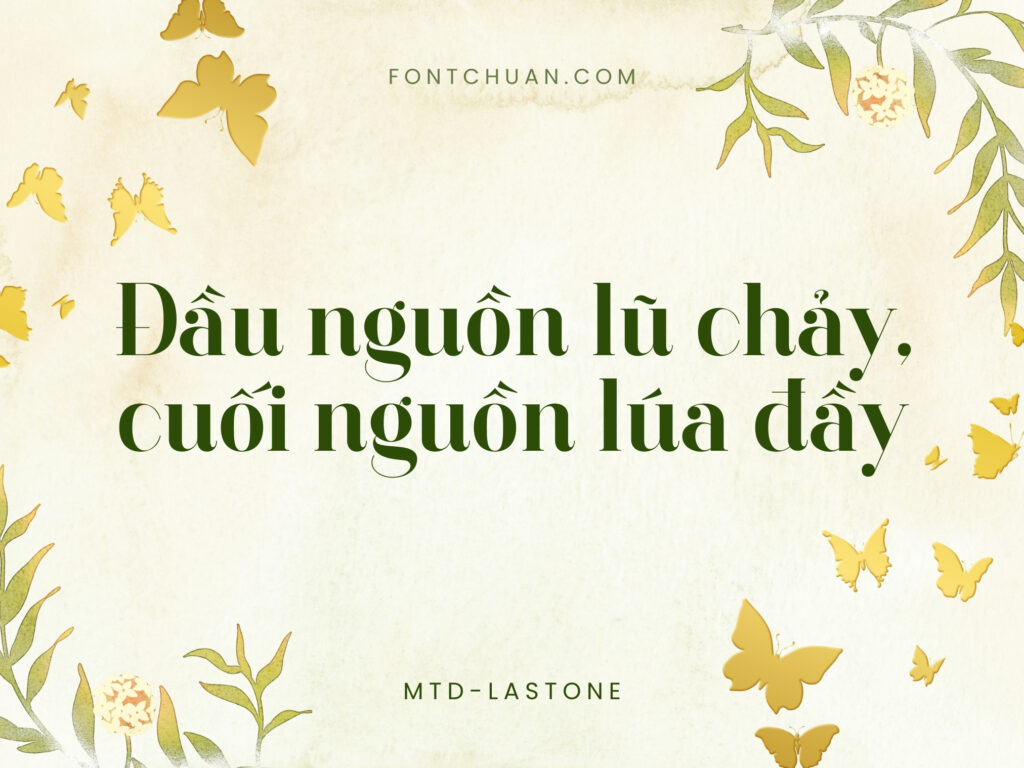
Font MTD Lastone Việt Hóa
Font MTD Lastone là một kiểu chữ hiển thị độc đáo mang hơi hướng hiện đại pha lẫn cổ điển, được thiết kế bởi Drizy Studio và Việt hóa bởi Mộc Hạ. Font hỗ trợ đầy đủ tiếng Việt và hơn 90 ngôn ngữ khác, tạo điều kiện thuận lợi cho việc sử dụng trong nhiều loại dự án thiết kế quốc tế. Font này đã được các thành viên của Font Chuẩn chọn lọc và ứng dụng vào thực tế thiết kế, đặc biệt trong các lĩnh vực sáng tạo cần sự mới lạ và cá tính thị giác.
MTD Lastone gây ấn tượng mạnh bởi các đường nét cứng cáp, hình khối vững chắc và sự cân đối trong cấu trúc ký tự, tạo nên một cảm giác mạnh mẽ và thẩm mỹ cao. Font rất phù hợp để sử dụng cho logo, tiêu đề poster, bìa sách, bộ nhận diện thương hiệu hoặc các sản phẩm thời trang và mỹ thuật. Các ngành nghề lý tưởng bao gồm quảng cáo, công nghệ, giáo dục, thiệp cưới và ảnh cưới. Font cũng được áp dụng hiệu quả trong các sự kiện như Tết, Giáng sinh, Valentine hoặc các dịp lễ hội nhấn mạnh yếu tố nghệ thuật và sáng tạo.